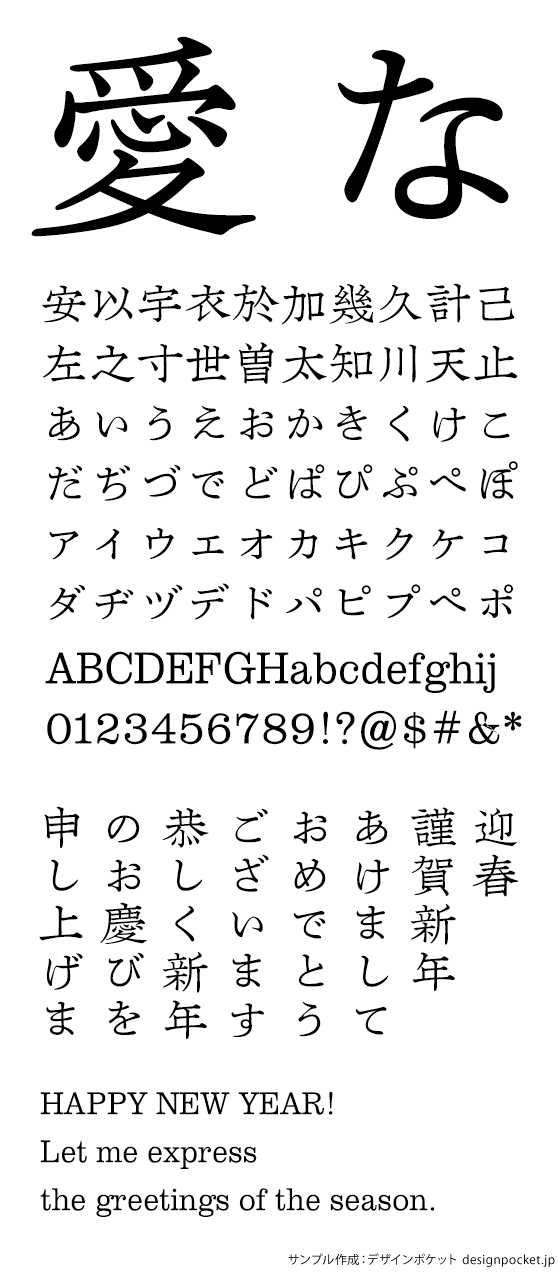
アンチック体
KOことのは方広M
KOKotonohaHoko-M
『辞苑』(新村出編、博文館、1935)の見出し語から復刻した和字アンチック体「ことのは」に、北宋代の仏教経典『大方廣佛華巖経』(龍興寺、990–994)にもちいられた字様をもとに翻刻した中世安竹体「方広」、ロバート・ベズリによる「クラレンドン」が掲載されている『印刷活字総合見本帳』(ファン・ストリート活字鋳造所、1857年)所収の見本から復刻したスラブセリフ体「K.E.Pisces」を組み合わせたKOことのは方広BKのファミリーで、メディウム・ウエイトです。
※「方広M」の漢字は第一水準限定です。